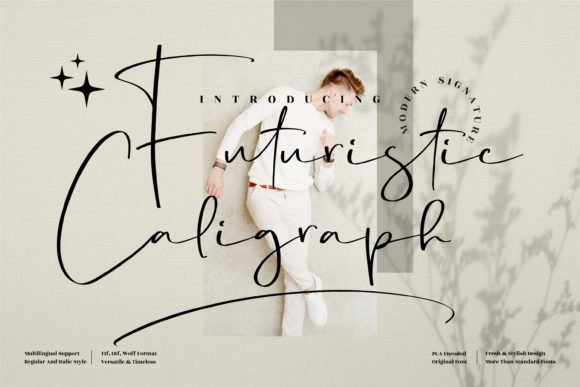
Futuristic Caligraph - ослепительный шрифт с тонким начертанием.
Этот шрифт отличается аккуратностью и высокой детализацией.
Независимо от темы, Futuristic Caligraph станет прекрасным дополнением к вашей библиотеке шрифтов, поскольку он способен улучшить любое творение.